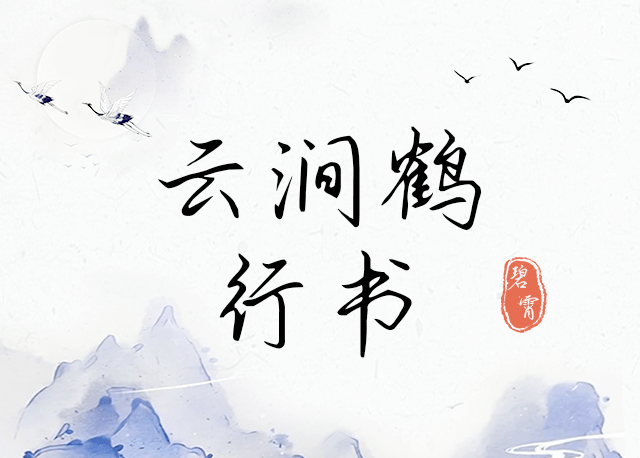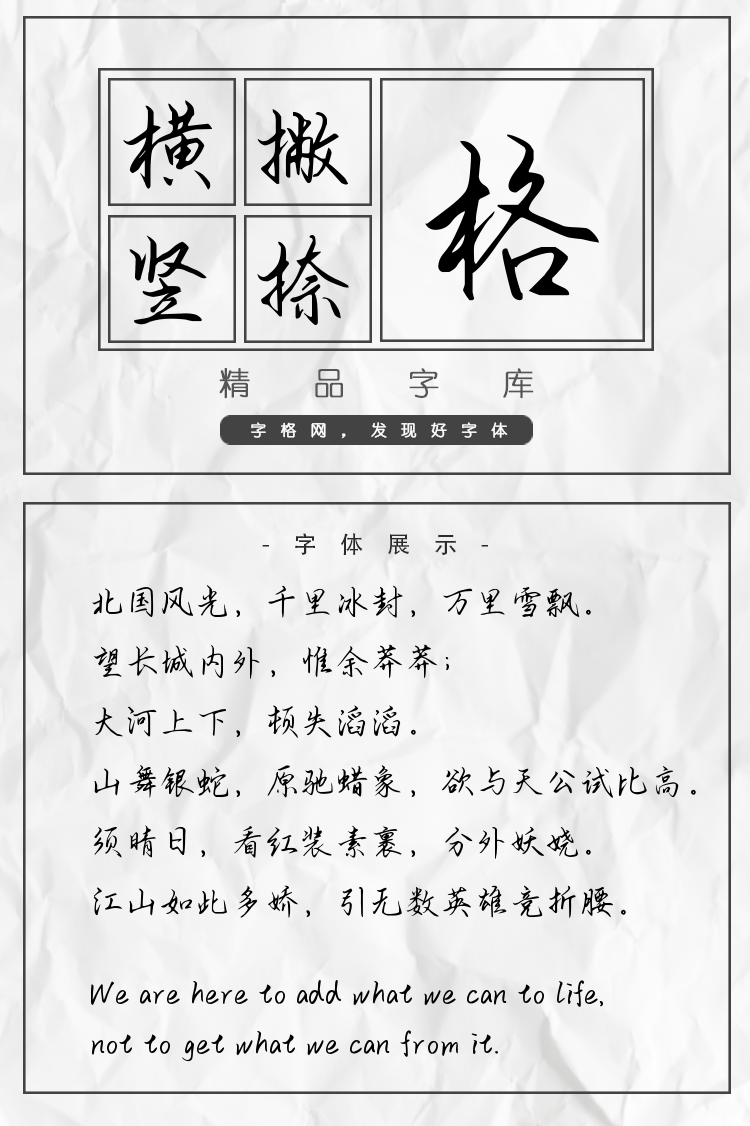
Aa云间鹤行书
字体说明:Aa云间鹤行书字体是一款可商用的毛笔书法,英文手写,手写体字体,该字体包含6763个中文、字母、符号和数字,具有充满力量、大气、豪放、稳重、手写风、古典 的风格,可以满足您设计上的各种需求,该字体主要用于电商、广告、视频影视、海报企宣、书籍 等场景, 您不但可以在字格网下载Aa云间鹤行书,同时还有众多毛笔书法字体、创意字体等可供选择!